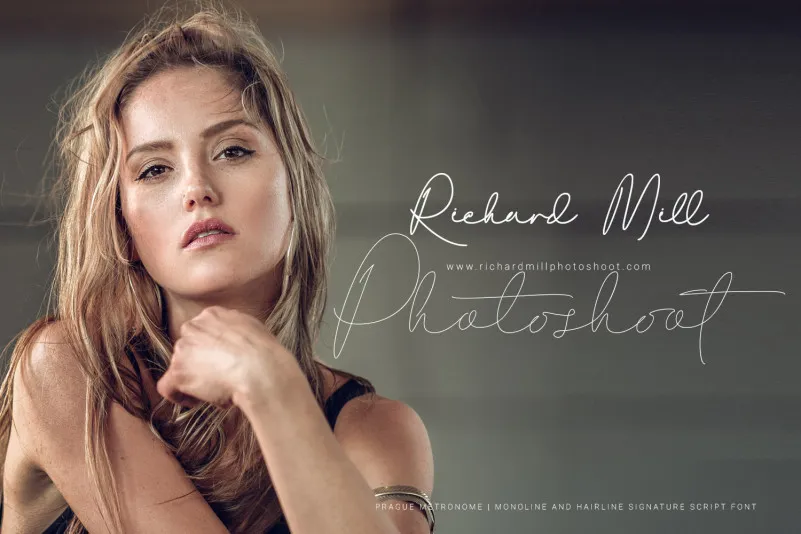
Prague Metronome Signature Font – Download Grátis
A fonte Prague Metronome Signature Font é uma delicia para os amantes do design gráfico e da arte urbana, inspirada na bela cidade de Praga. Embora a font tenha um gosto claro e único, ela está muito além do que simplesmente ser uma fonte. Ela reveste-se da essência praguense, capturando o movimento vibrante e a história imortalizada nas paredes desta cidade mágica. Desenvolvida pelo criador talentoso da 38.lineart, esta font vem com um toque de originalidade que não se encontra facilmente em outras. É perfeitamente adequada para trabalhos artísticos inspirados na arte do design gráfico, especialmente aqueles que valorizam o uso de fontes manuscritas. E como sua descrição sugere, ela traz à vida a essência da metade urbana e da natureza ao encontro em Praga. Adquirir Prague Metronome Signature Font é, portanto, não apenas adquirir uma fonte; é capturar um pedacinho do encantamento praguense em cada letra. Este é o tipo de detalhe que transforma um design simples em algo memorável e único.